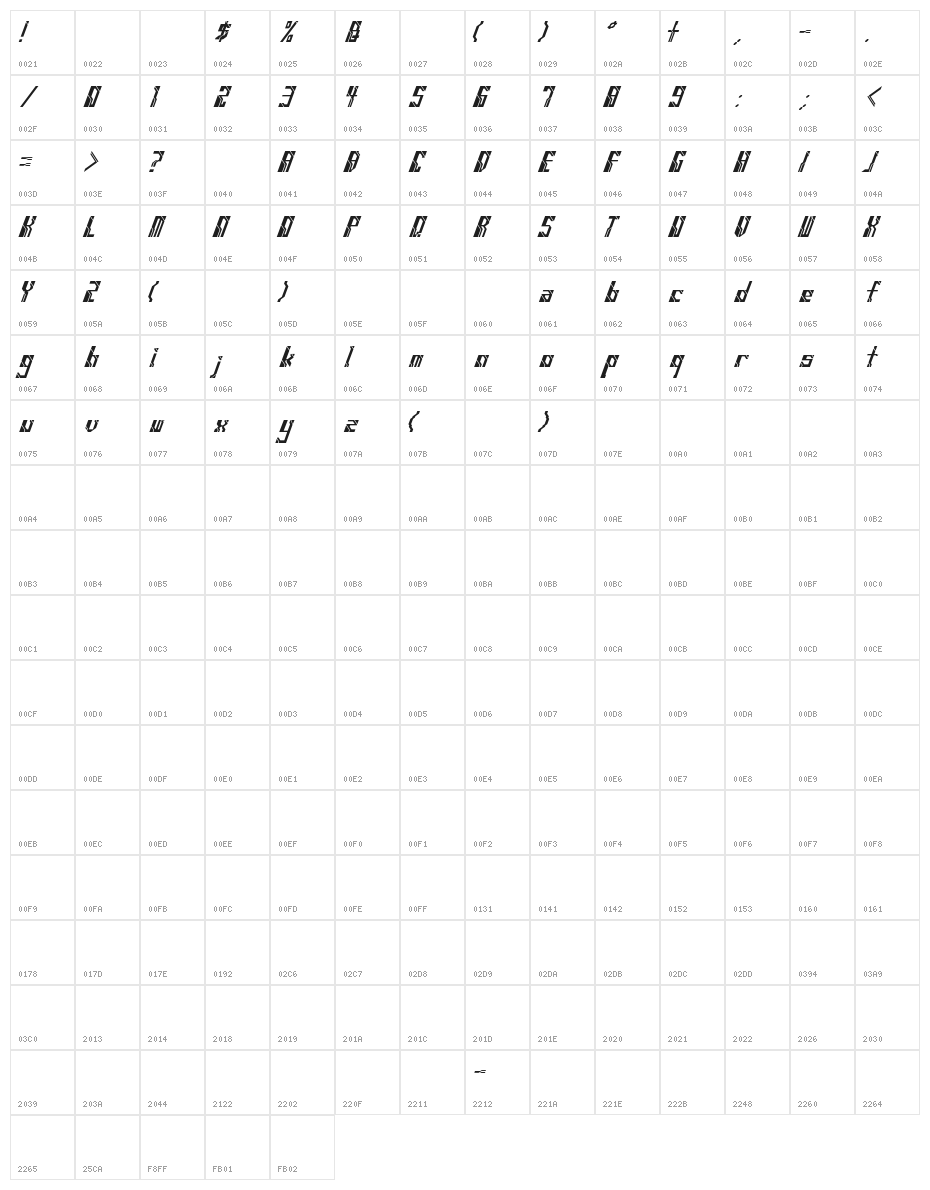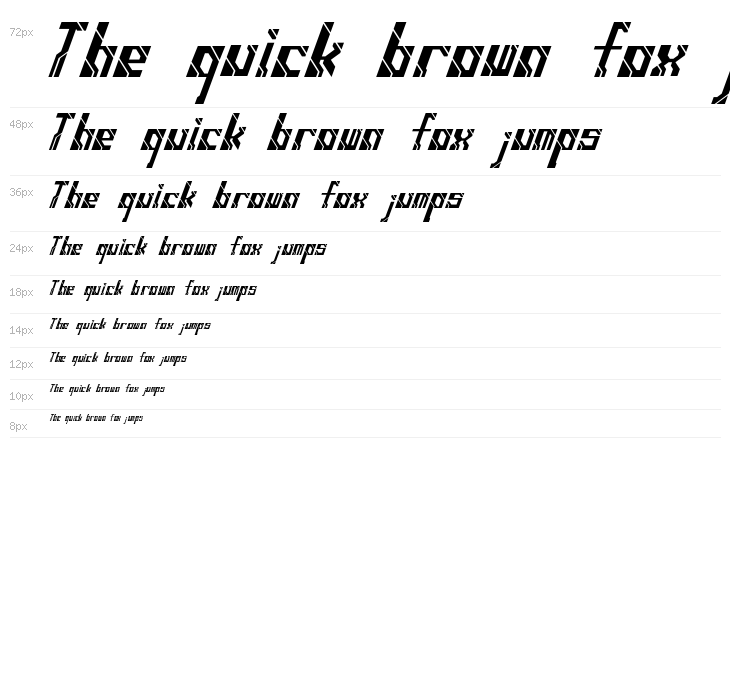
NIALE Font
✎ Futuristic
| مشاريع مقترحة | Ideal for sci-fi themed projects, video game titles, posters, and branding that requires a modern and edgy aesthetic. |